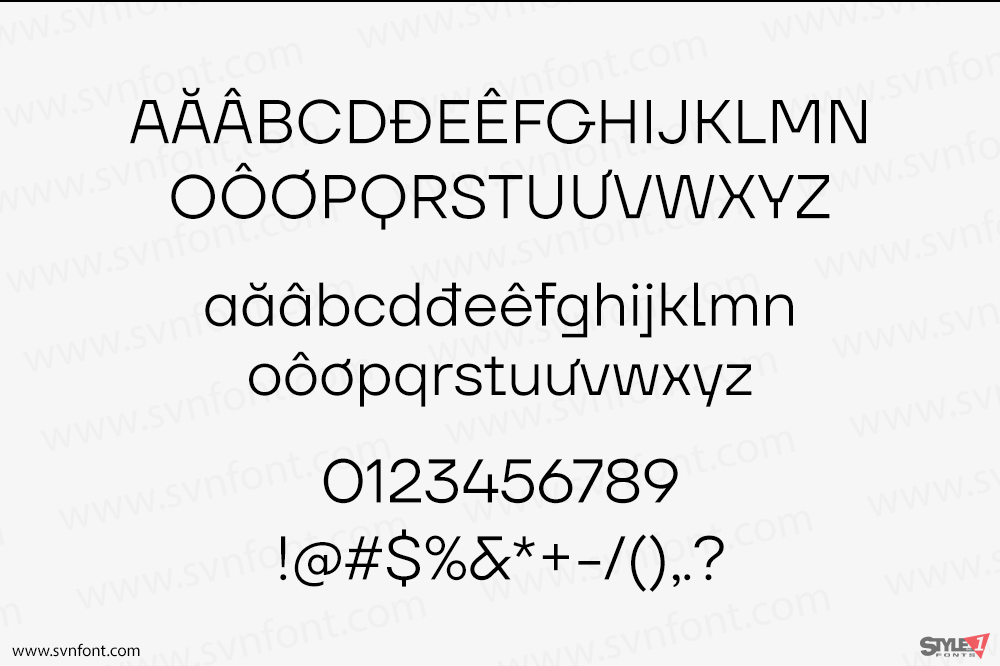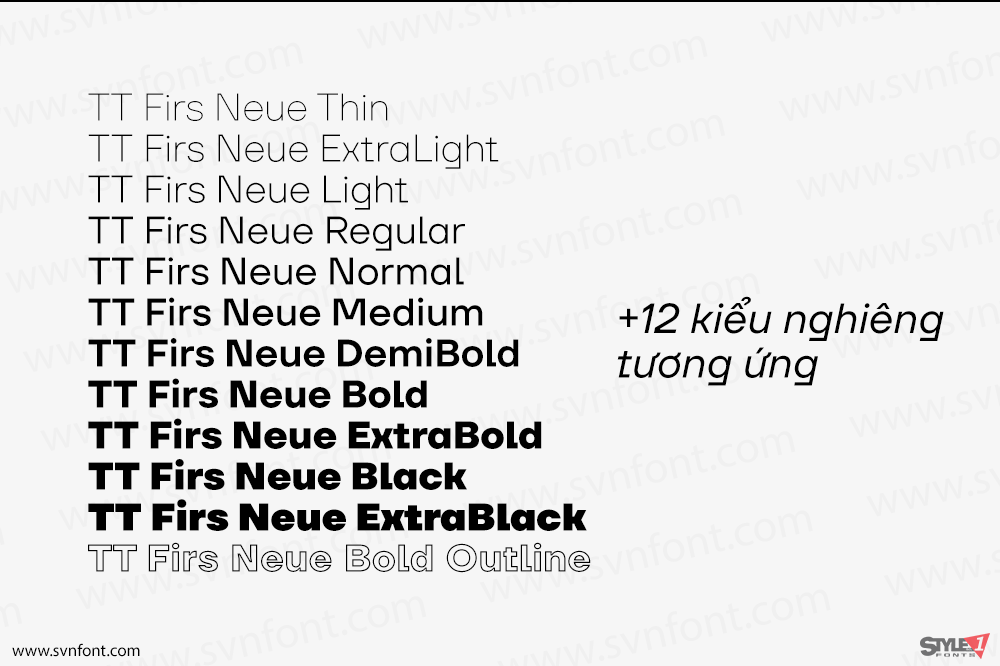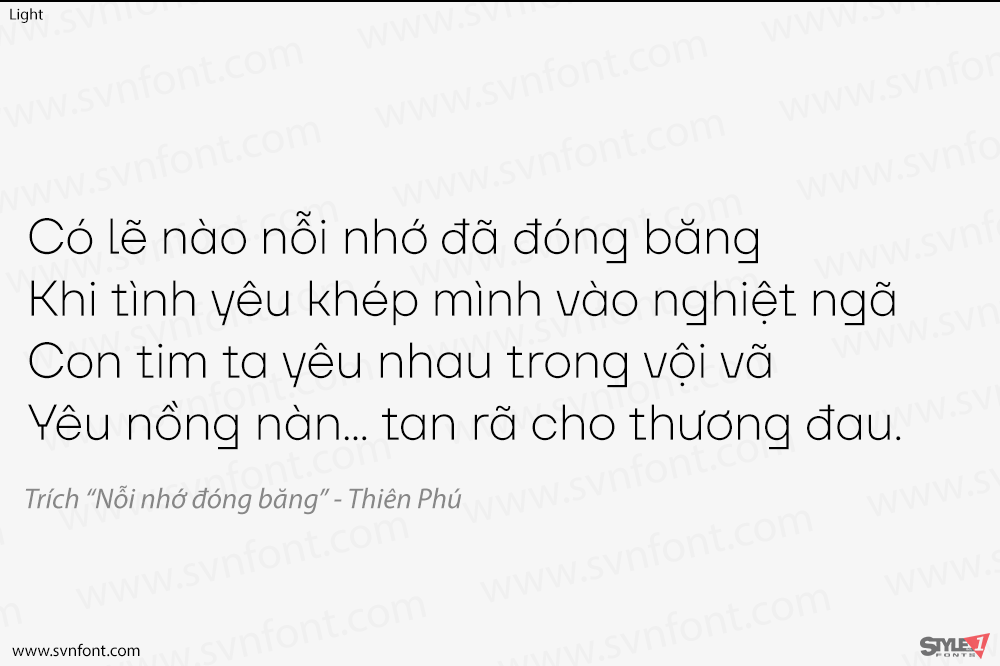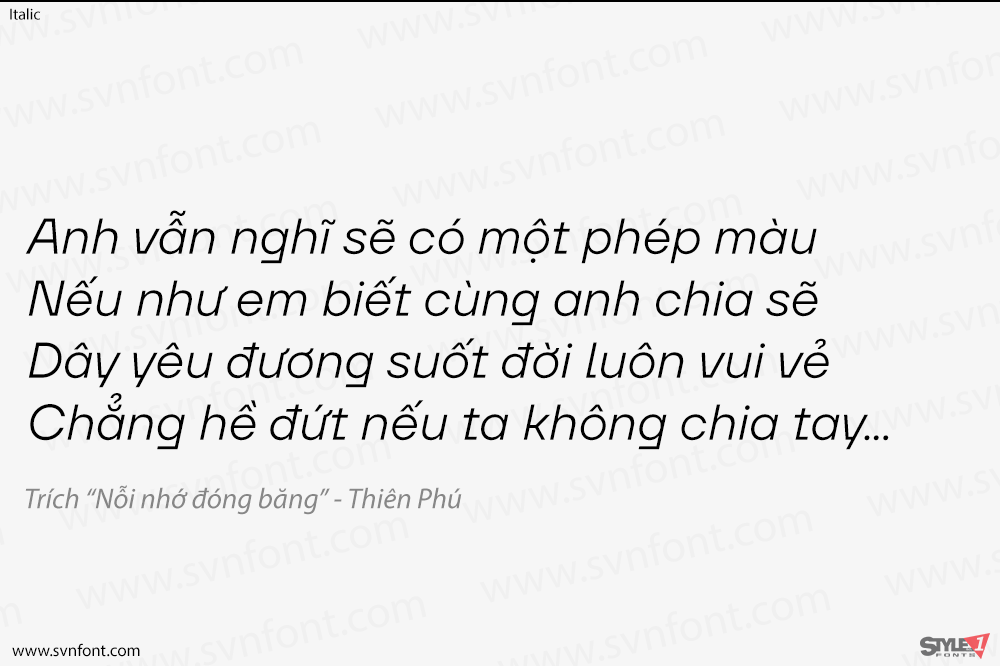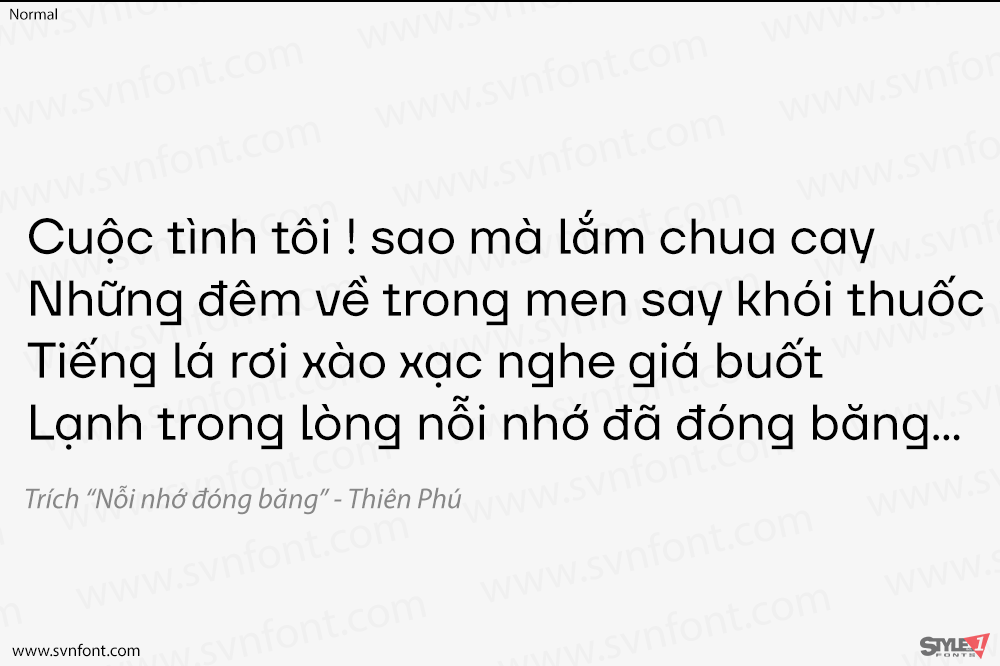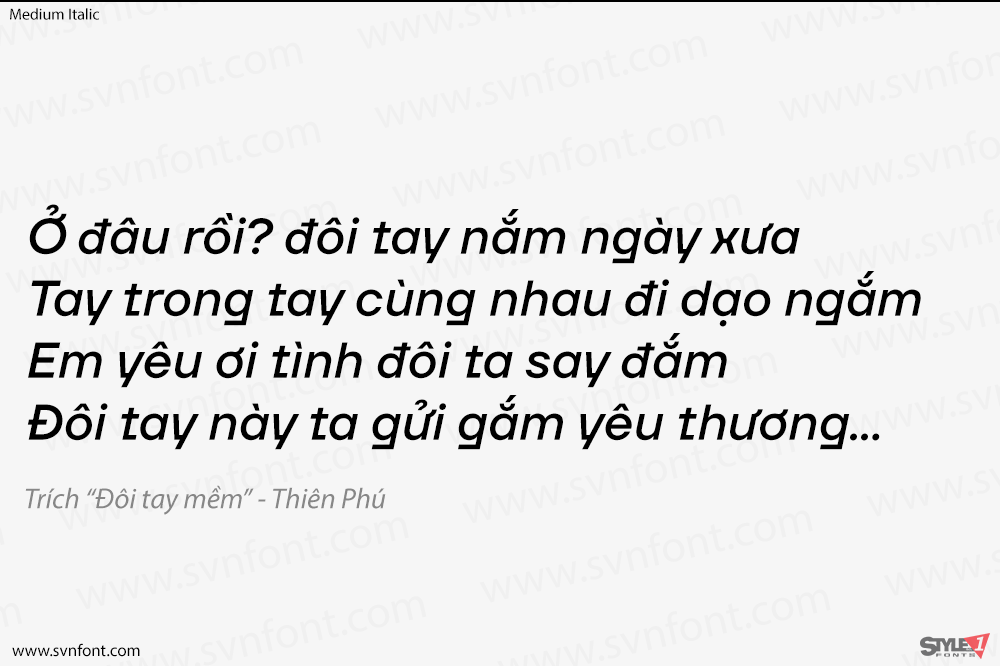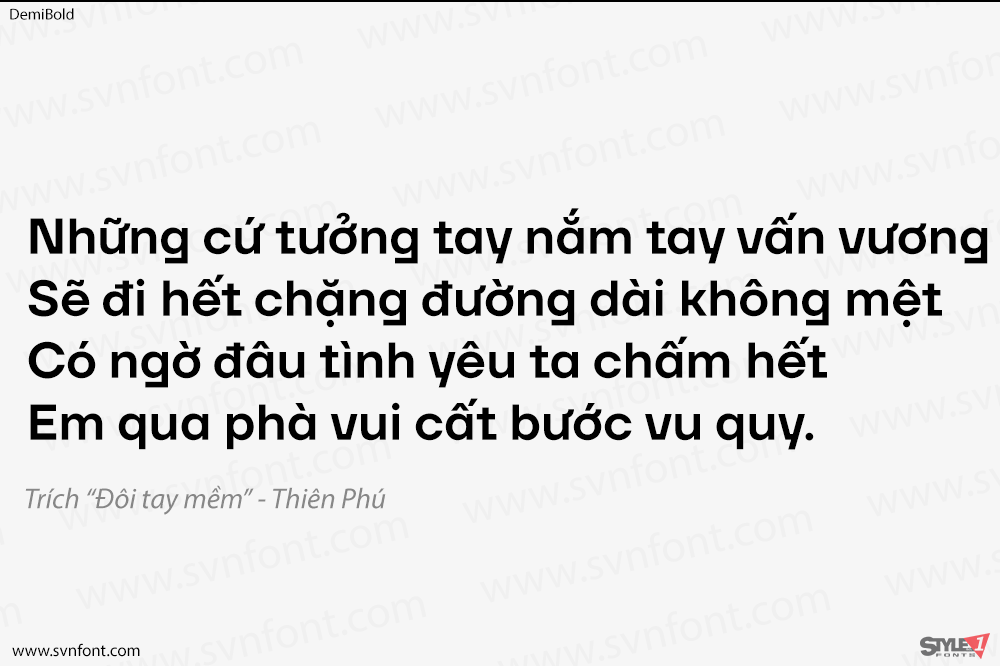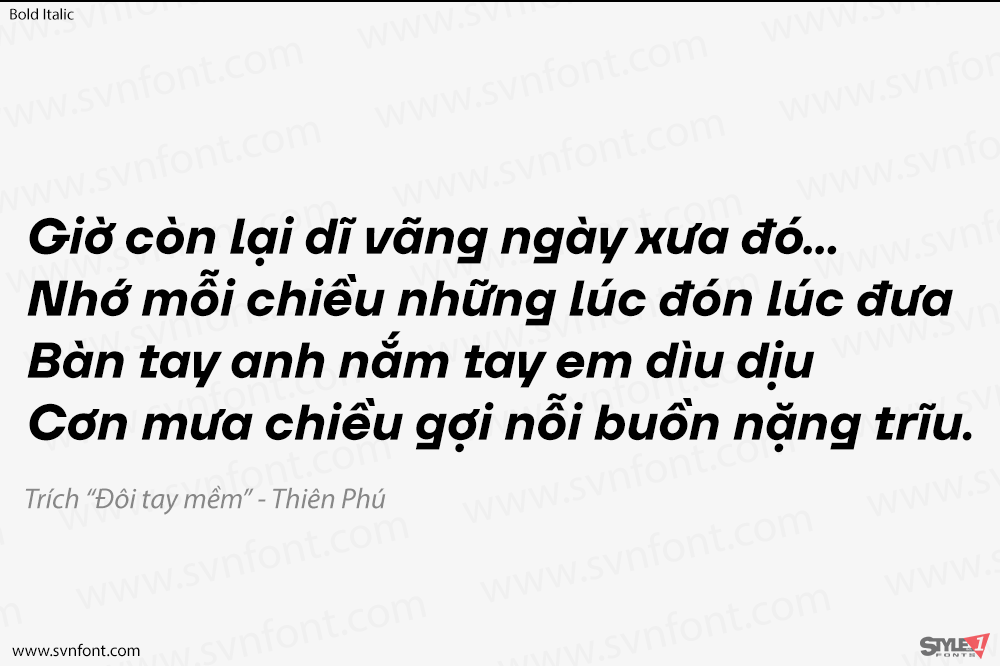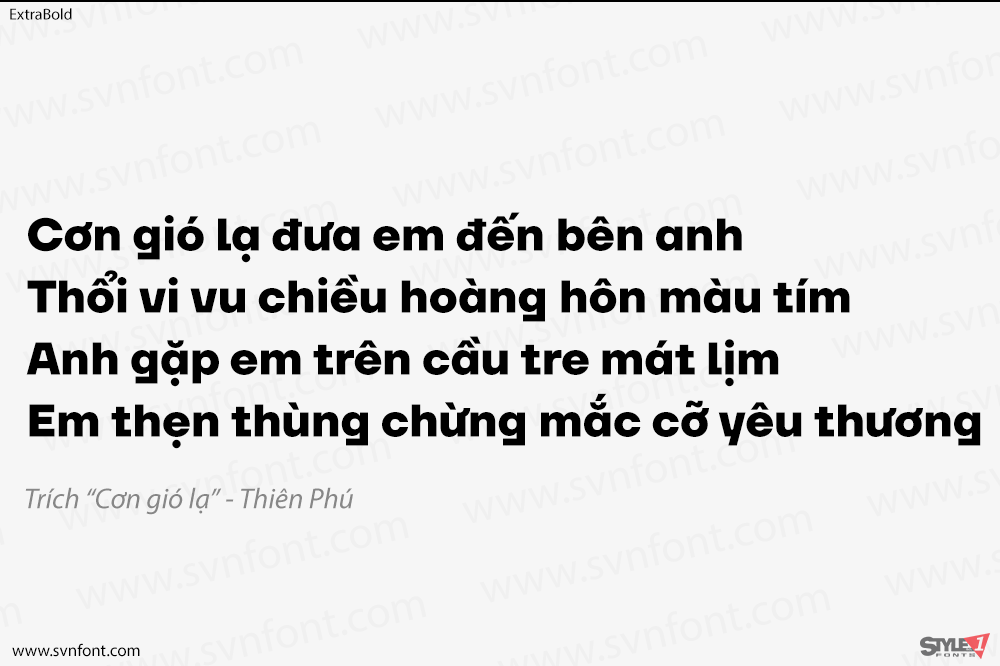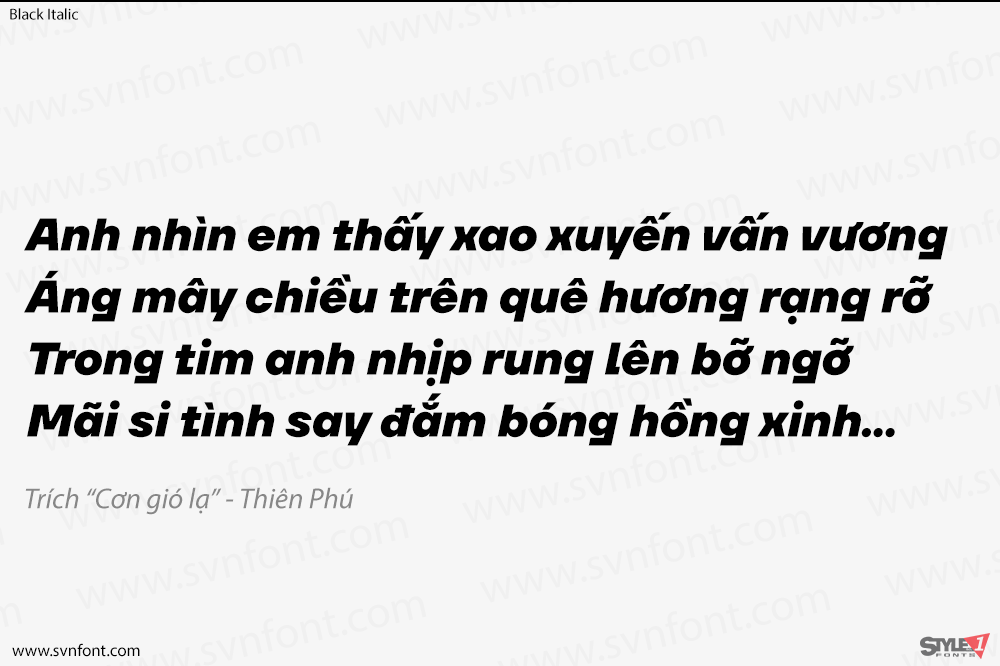
TT Firs Neue là một phông chữ sans serif kết hợp các yếu tố đồ họa biểu cảm với tính linh hoạt trong sử dụng. Trong phiên bản mới nhất năm 2023, các yếu tố hiển thị của phông chữ đã trở nên hấp dẫn hơn, đồng thời sự cân bằng tổng thể của phông chữ cũng được cải thiện. Đây là kết quả của nghiên cứu thị giác mà chúng tôi đã thực hiện trước khi tiến hành cập nhật.
Chúng tôi vẫn giữ tình cảm ấm áp đối với thành công trước đây của TT Firs Neue đồng thời thiết kế lại phông chữ và thực hiện những thay đổi đáng kể. Phông chữ phiên bản 2023 đã được phát triển theo các tiêu chuẩn kỹ thuật mới, vốn đã cao hơn đáng kể trong 5 năm qua.
TT Firs Neue là một phông chữ phù hợp với nhiều bối cảnh khác nhau. Nó có thể được sử dụng cho tiêu đề, đoạn văn bản, trưng bày trực quan và trang trí tòa nhà, cũng như trên web. Phông chữ này mang tính thẩm mỹ cao trên ảnh bìa podcast và video, đồng thời là một lựa chọn lý tưởng cho thiết kế bao bì và nhận diện thương hiệu.
Nhà thiết kế: Antonina Zhulkova, Marina Khodak, TypeType Team